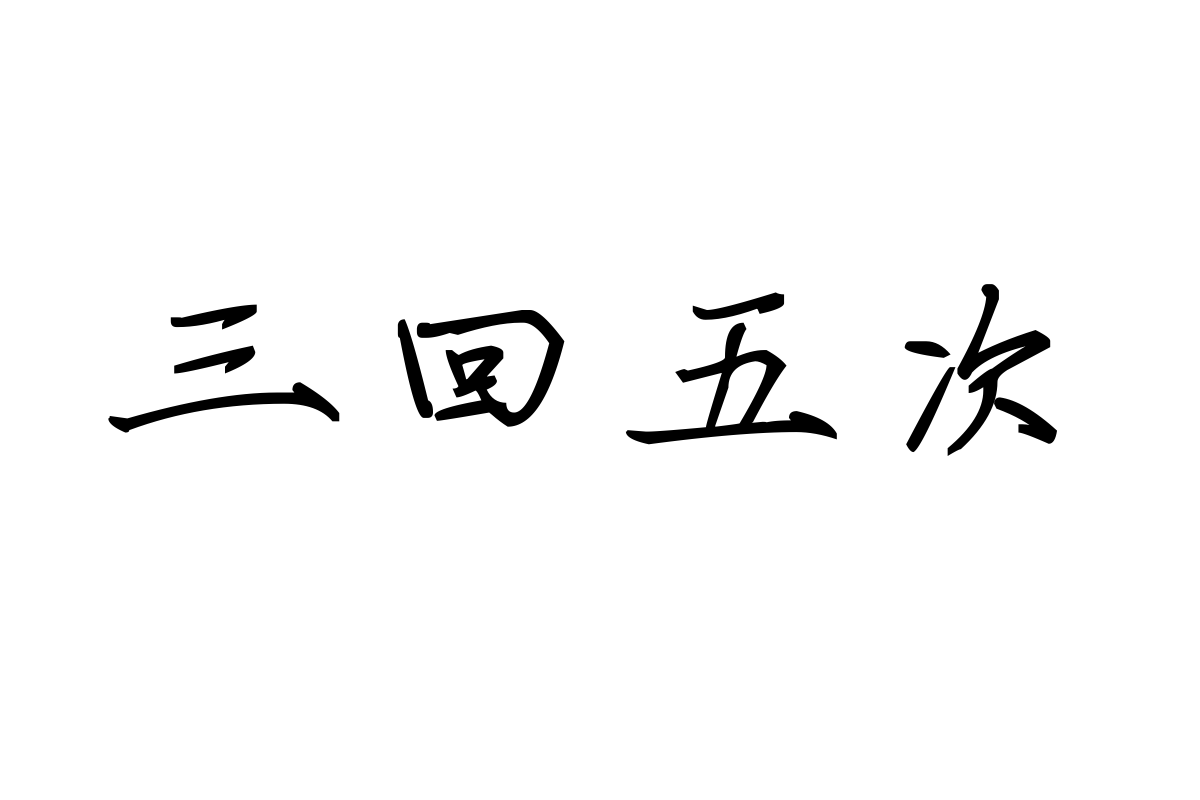
也字工厂清朗瘦金体,是一款专为中文设计的艺术字体。它以简洁明快的线条和优雅的字形结构为特点,适合用于各种需要展示文字美感的场景。
这款字体的特点是笔画流畅,结构紧凑,既保留了传统书法的韵味,又融入了现代审美的元素。它的字形大小适中,易于阅读,同时在视觉上也能产生良好的平衡感。无论是标题、正文还是装饰性的文字,都可以通过这款字体展现出独特的艺术效果。
此外,也字工厂清朗瘦金体还具有很好的可读性和易用性。它的每个字符都有明确的边界,使得文字的排列更加整齐有序。同时,这款字体还支持多种字体样式的选择,可以根据不同的需求进行个性化的设计和调整。
总的来说,也字工厂清朗瘦金体是一款非常适合现代设计的字体,无论是用于印刷品、网页设计还是其他任何需要展示文字美感的场景,它都能发挥出出色的效果。